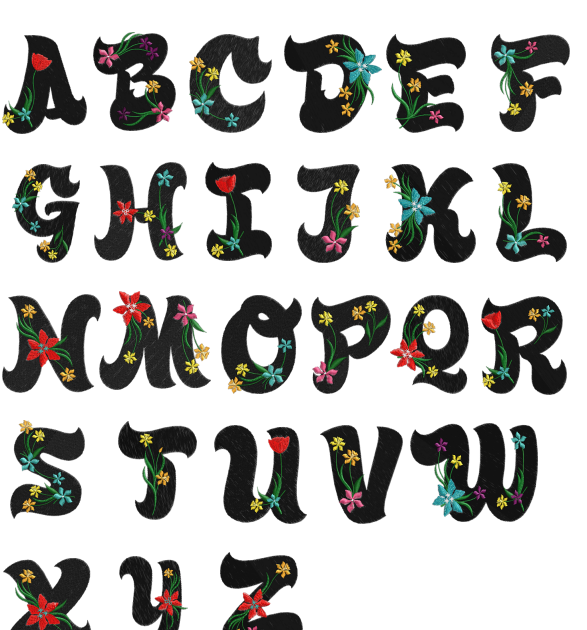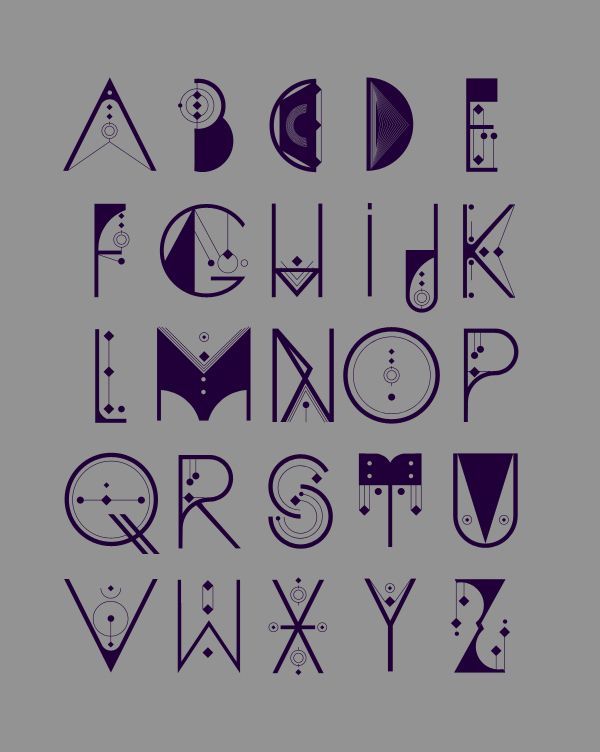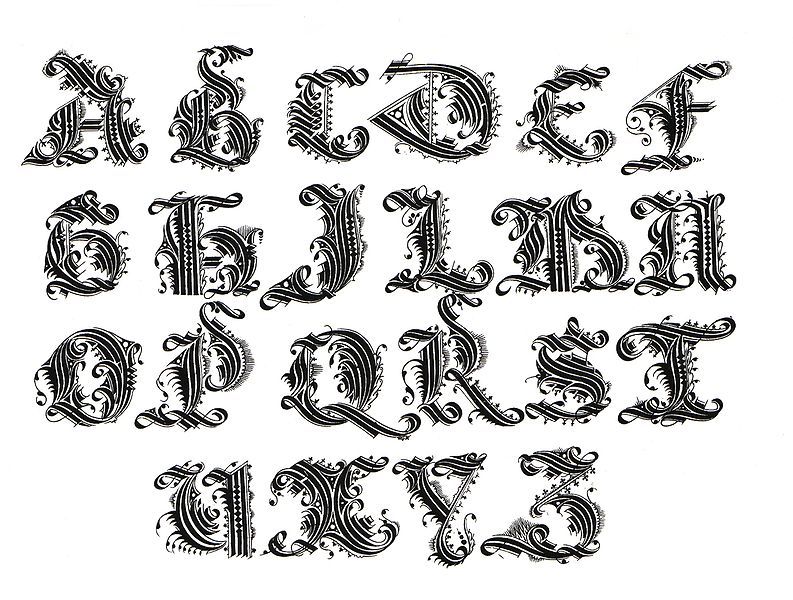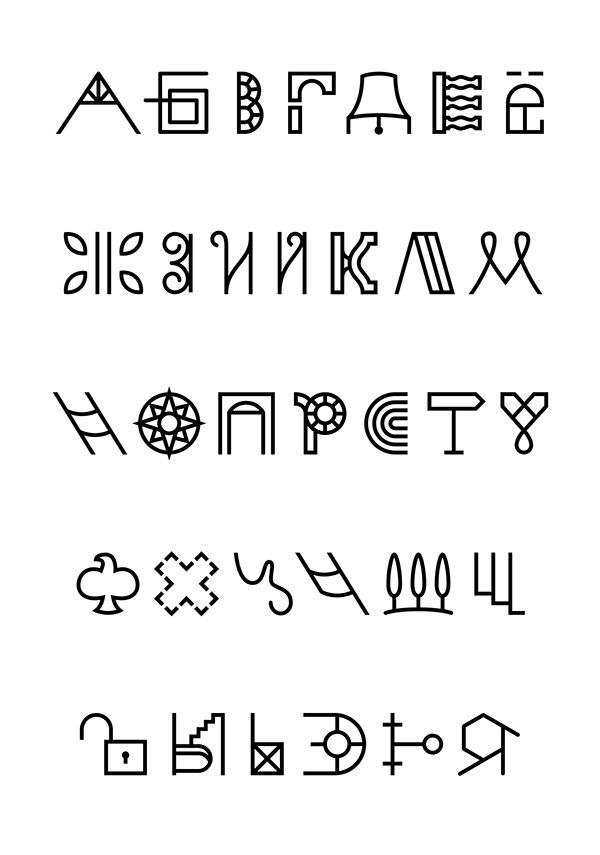
Необычный шрифт букв русского алфавита: шаблоны букв, распечатать и вырезать. Яп
Каллиграфический шрифт картинки — 85 фото
Шрифты для Pilot Parallel Pen
Современная русская каллиграфия
Каллиграфический почерк алфавит для начинающих
Леттеринг буквы русского алфавита
Стили шрифтов для тату
Каллиграфия плакат
Каллиграфия Готика фрактура
Кисть для каллиграфии
Стилизованный шрифт
Каллиграфический шрифт
Каллиграфия кириллица скоропись
Каллиграфические имена на русском
Шрифт каллиграфия кистью кириллица
Леттеринг алфавит английский
Почерк спенсериан
Каллиграфический шрифт Готика
Каллиграфический шрифт цифры
Каллиграфия английский алфавит копперплейт
Каллиграфический шрифт
Современная каллиграфия шрифты
Каллиграфический шрифт
Современная каллиграфия
Каллиграфия копперплейт алфавит
Шрифты леттеринг Готика
Каллиграфический почерк с завитушками
Cursive шрифт
Каллиграфические надписи
Каллиграфия шрифт
Каллиграфия копперплейт алфавит
Каллиграфия брашпеном алфавит
Каллиграфия пером шрифт
Каллиграфия буквы покрас Лампас
Каллиграфический шрифт
Каллиграфия копперплейт алфавит
Шрифт каллиграфия кистью кириллица
Копперплейт шрифт каллиграфия
Леттеринг Готика алфавит
Спенсериан каллиграфия
Каллиграфический шрифт
Фрактура каллиграфия
Каллиграфический почерк алфавит
Каллиграфия в стиле Готика для алфавит
Буквы каллиграфическим почерком русские
Каллиграфический шрифт русский
Каллиграфия русский алфавит прописи
Флориш Готика каллиграфия
Буквы каллиграфическим почерком русские
Шрифты для тату
Красивый шрифт
Каллиграфические буквы английские
Алфавит спенсериан каллиграфия
Каллиграфический почерк английский алфавит
Каллиграфия русского алфавита строчные буквы
Леттеринг на английском Готика
Каллиграфия итальянский курсив прописи
Стиль леттеринг шрифты
Каллиграфия необычные шрифты
Красивая буква а заглавная каллиграфия
Шрифты леттеринг ручкой
Каллиграфия английский алфавит копперплейт
Красивый шрифт на английском
Шрифты для тату
Каллиграфия копперплейт алфавит
Русский алфавит спенсериан каллиграфия
Английские буквы красивым шрифтом
Татарский шрифт
Готический почерк английский
Шрифт копперплейт кириллица каллиграфия
Каллиграфия копперплейт алфавит
Красивый прописной почерк алфавит
Красивые прописные буквы по английскому
Каллиграфия английский алфавит копперплейт
Красивые английские буквы
Шериф красивый на русском
Скоропись каллиграфия алфавит
Каллиграфия английский алфавит копперплейт
Прописи для красивого почерка
Рукописные русские шрифты кистью
Каллиграфические буквы
Шрифт в арабском стиле
Каллиграфичное правописание букв
Spencerian каллиграфия
Каллиграфия Готика фрактура
Каллиграфический шрифт современный
Покрас Лампас каллиграфия алфавит
emailОдна из самых серьезных проблем при создании электронных писем — правильно выбрать шрифт. Вес, высота, ширина, цвет, форма, интервал… Все ли здесь имеет значение? Да, важно все, но самое главное — выбрать читабельный шрифт.
В этой статье мы расскажем, как выбрать лучший профессиональный шрифт для рассылки.
Шрифты HTML-писем: основные правила, которые нужно соблюдать
При выборе оптимального шрифта следует учитывать три базовых правила:
1. Не используйте более двух шрифтов
Если вы используете слишком много шрифтов, ваше письмо будет выглядеть как минимум перенасыщенным, а в худшем — довольно раздражающим. Для одного письма достаточно одного или двух шрифтов. В идеале вообще используется всего один шрифт, но разных размеров: больший — для заголовков, а меньший — для остального контента.
2.
Избегайте применения более двух стилей шрифтаНе смешивайте в письмах обычные, жирные и курсивные стили шрифтов. Если вы используете более двух, рассылка будет выглядеть неаккуратно. Как правило, достаточно одного стиля. Если же вы хотите что-то выделить, можно применить жирный шрифт.
При этом никогда не подчеркивайте текст и не используйте курсив — это противоречит правилам доступности писем.
3. Уделите особое внимание читабельности выбранного шрифта
Основной параметр шрифта вашего контента — читабельность. Это понятие означает возможность отличить одну букву от другой. Естественно, разборчивый текст лучше и быстрее читается, поэтому проверьте, все ли символы четкие, хорошо заметные и различимые.
Какой шрифт самый читаемый? В 2010 году Норберт Шварц и Хюнджин Сонг провели эксперимент по разборчивости шрифта. Результаты были впечатляющими: чтение курсивных и декоративных шрифтов отнимает почти вдвое больше времени, чем стандартных и легко читаемых:
И еще о разборчивости.
.. Существуют два основных типа шрифтов: с засечками и без. Давайте посмотрим, какой из них лучше использовать для email-рассылок.
Какой шрифт выбрать: с засечками или без?
Да, эти типы (гарнитуры) тоже влияют на разборчивость шрифтов электронных писем. В чем заключается разница между ними?
Шрифты Serif (с засечками) можно определить как шрифты с маленькой черточкой в конце каждого символа. Самые популярные шрифты с засечками — Times New Roman и Georgia.
Шрифты Sans Serif (без засечек) — это те, которые не имеют такой декоративной линии в конце символа. Самые популярные веб-безопасные шрифты такого типа — Arial, Trebuchet MS и Helvetica.
В ходе своего исследования я нашла ряд источников, которые утверждают, что шрифты с засечками лучше подходят для рассылок, но я с этим категорически не согласна. Если предположить, что письма просматриваются только в режиме онлайн на десктопных или мобильных экранах, то лучше всего использовать шрифты без засечек — такие символы проще читать с экрана.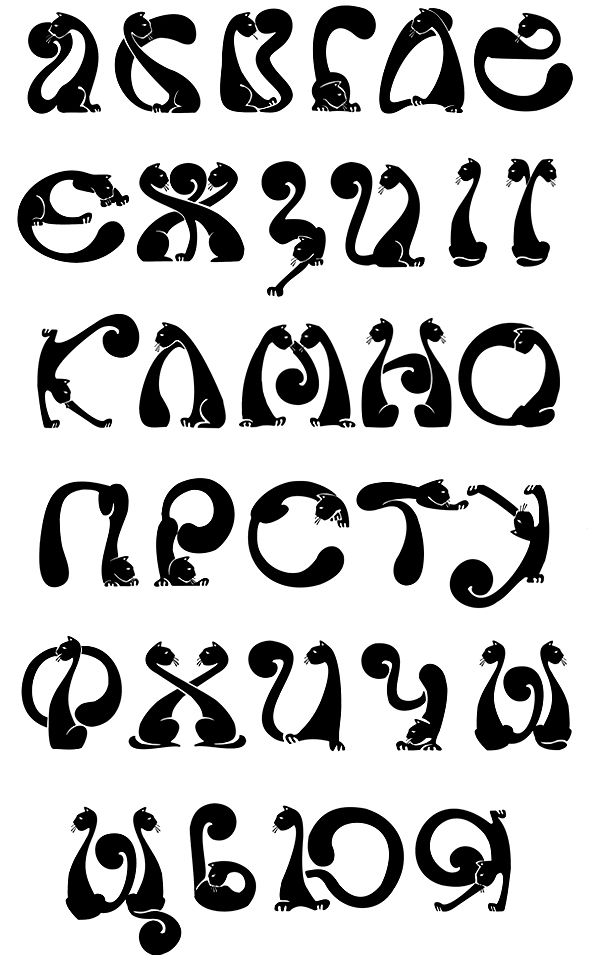
Безопасные шрифты для писем
Вашему вниманию предлагается список из 10 лучших шрифтов, которые можно использовать со 100% гарантией того, что они будут отображаться в электронных ящиках пользователей именно так, как было задумано. Поэтому вы можете спокойно выбрать из этого списка веб-шрифт для своих нужд:
1. Шрифт для писем Arial
Этот шрифт, разработанный еще в 1982 году, входит в пакеты всех версий Microsoft, начиная с Windows 3, и Apple Mac OS X. Отображается всеми почтовыми клиентами. Благодаря терминальным диагональным разрезам выглядит менее механическим по сравнению с другими sans serif.
2. Шрифт для писем Helvetica
Печатный шрифт sans-serif, один из самых применяемых шрифтов, имеет закругленные буквы и широкие прописные буквы. Разработан в 1957 году.
3. Шрифт для писем Times New Roman
Этот безупречный шрифт имеет высокие строчные буквы, слегка уплотненные, короткие нисходящие и восходящие. Создан по заказу газеты «The Times» в 1931 году.
Это один из любимых шрифтов из семейства sans serifs у многих интернет-пользователей и веб-дизайнеров.
4. Шрифт для писем Verdana
Он был разработан для чтения на экранах с низким разрешением. Его главная особенность — высокие и широкие строчные символы.
5. Шрифт для писем Courier / Courier New
Courier был разработан в 1955 году и адаптирован для моноширинного шрифта. Courier New имеет больше точек и запятых, чем оригинальный Courier. Courier является стандартным современным шрифтом, используемым для написания сценариев в киноиндустрии.
6. Шрифт для писем Tahoma
Он похож на Verdana, но имеет более узкие буквы, маленькие кегли и малый интервал между буквами. Используется в качестве экранного шрифта по умолчанию в версиях Windows 95, 2000 и XP.
7. Шрифт для писем Georgia
Он имеет высокие строчные штрихи, которые толще среднестатистических, его цифры органично сочетаются с текстом благодаря одинаковому размеру.
8. Шрифт для писем Palatino
Этот великолепный шрифт был изначально разработан для заголовков, рекламных объявлений и печати. Он шире других шрифтов serif старого стиля и прекрасно подходит для дизайна логотипов.
9. Шрифт для писем Trebuchet MS
Имеет укороченные хвосты для некоторых букв; в полужирном начертании буквы заостренные, а не закругленные, и закругленные точки в прописных и строчных буквах. Появился в 1996 году.
10. Шрифт для писем Geneva
Это обновленная версия Helvetica. Его главное отличие — наличие базового набора лигатур.
Эти шрифты считаются самыми читаемыми современными шрифтами и одними из лучших современных шрифтов для использования в email-дизайне.
Кастомные шрифты
Бывает так, что вы хотите — или должны — использовать в письме собственный уникальный шрифт. Например, для соблюдения стиля бренда. Или если нужно создать праздничное письмо для соответствующего случая.
Напоминаем, что вы можете загружать кастомные шрифты в свой аккаунт Stripo и использовать их в рассылках.
Используйте кастомные шрифты в рассылках — соблюдайте стиль бренда
Присоединяйтесь к Stripo
Но при этом мы настоятельно рекомендуем предварительно тестировать их отображение в различных комбинациях почтовиков, девайсов и ОС. Это можно сделать при помощи нашего встроенного инструмента тестирования.
Важно отметить:
Если почтовый клиент не поддерживает какой-либо шрифт, то последний не будет отображаться неправильно — он просто будет заменен дефолтным шрифтом.
Вот список дефолтных шрифтов для самых популярных почтовиков:
-
iCloud Mail использует Helvetica в качестве дефолтного;
-
Gmail применяет Arial;
-
Microsoft Outlook самых доисторических версий часто использует Calibri;
Размер шрифта
Не существует такого понятия, как лучший размер шрифта. Дело в том, что разные шрифты часто имеют разную высоту символов.
В результате один и тот же размер, к примеру 16 пикселей, выглядит очень неодинаково в зависимости от выбранного семейства шрифтов.
Я создала в редакторе Stripo специальный шаблон, который позволяет сравнить разные шрифты одних и тех же размеров. Вот результаты:
Выберите любой из них на ваш вкус и используете во всех электронных email-кампаниях, чтобы ваши письма всегда были разборчивыми и соответствовали стилю бренда.
Мы советуем сразу выбирать шрифты и их размеры, как только вы начинаете работу с новым шаблоном — настройки будут применены сразу ко всему письму. Это существенно сэкономит время, так как вы избавитесь от необходимости настраивать шрифт для каждой части письма.
Знаете ли вы, что в Stripo можно устанавливать разные размеры шрифтов для мобильных и десктопных устройств? Например, вы используете 14 пикселей для десктопной версии и 16 пикселей, если письмо открывается на смартфоне.
Настройка размера шрифта для десктопных устройств
-
войдите во вкладку «Оформление»;
-
перейдите в раздел «Общие настройки»;
-
выберите нужный шрифт в выпадающем меню.
Кастомные шрифты, которые вы ранее добавили в свой профиль Stripo, тоже отобразятся в этом списке; -
установите межстрочный интервал;
Попробовать Stripo
Настройка размера шрифта для мобильных
-
зайдите во вкладку «Оформление»;
-
перейдите в раздел «Адаптивность»;
-
установите размеры шрифта для хедеров и футеров, областей контента, пунктов меню и кнопок.
Поработайте над отображением ваших писем на мобильных, и они будут легко читаемыми на любом устройстве
Присоединиться к Stripo
Межстрочный интервал
Межстрочный интервал — это расстояние между строками по вертикали. Он измеряется в процентах от размера шрифта.
Вы можете установить желаемый интервал для своих писем в тех же вкладках и разделах, в которых только что настроили размер шрифта.
Некоторые источники утверждают, что лучший межстрочный интервал — 150%.
Но если учесть рекомендации по доступности писем, то оптимальный интервал варьируется от 150% до 200%.
(текст письма с одиночным интервалом)
(текст письма с интервалом 1,6)
Ссылки
Не стоит использовать другой шрифт, чтобы привлечь внимание читателей к ссылкам. И ни в коем случае не добавляйте ссылки без анкорного текста. Текст анкора должен пояснять, куда ведет данная ссылка, и быть органичной частью текста. Избегайте слов «здесь» или «ссылка» в качестве анкорного текста. Они слишком короткие и слишком общие, чтобы быть интересными.
Одно из лучших решений — сделать ссылки того же цвета, что и логотип. Это выглядит великолепно, вот посмотрите:
(Источник: письмо от Epilepsy Foundation)
Можно также подчеркнуть ссылки, если вы посчитаете это нужным или если такие ссылки соответствуют дизайну вашего письма.
Хотя из соображений доступности писем мы очень не советуем подчеркивать ссылки — это дезориентирует людей с дислексией.
Кнопки
Кнопки — это те же ссылки, но в более интерактивной для пользователей форме. Лучше использовать в письмах и ссылки, и кнопки. Если вы добавляете ссылку, которая приведет читателей к статье в блоге, вы можете сделать ее текстовой. Но если ссылка нужна, чтобы попробовать ваш продукт, то лучше использовать кнопки.
Что касается цвета кнопок, каких-то определенных правил здесь нет. Мы советуем положиться на цветовую психологию и постараться не разрушить концепцию дизайна слишком «кричащей» цветопередачей.
То же относится и к шрифтам для кнопок: четких правил не существует. Просто убедитесь, что тексты кнопок достаточно разборчивы.
Убедитесь, что цвет текста гармонирует с цветом кнопки и что он достаточно заметный и читаемый. Также проверьте, правильно ли расположен текст на кнопке — он не должен выползать за ее края.
Вот тот случай, когда кнопка смотрится отлично:
(Источник: email-шаблон Stripo)
Важно отметить:
При помощи Stripo в кнопки можно даже добавлять пробелы, чтобы между текстом и границами кнопки оставалось свободное пространство.
Это делает их более читабельными.
Как это сделать? Поработайте над параметрами внутренних отступов во вкладке «Кнопка».
Вы также можете отдельно настроить размер шрифта кнопок для мобильной версии.
Для этого вам нужно:
-
зайти во вкладку «Оформление»;
-
перейти в раздел «Адаптивность»;
-
установить размер текста кнопки, чтобы сделать его разборчивым на мобильных экранах. Оптимальный размер — 16px или крупнее;
-
включить «Кнопки на всю ширину», чтобы сделать кнопки шире на смартфонах. У полноразмерных кнопок больше шансов быть замеченными.
Делайте кнопки CTA заметными и интерактивными на любом устройстве
Присоединиться к Stripo
Текст поверх баннера
Это возможность использовать необычные и декоративные шрифты, которые вы не можете использовать как основной шрифт для текста.
А поскольку текст поверх баннера является частью изображения, то он не утратит своей декоративности ни в одном почтовом клиенте. То есть здесь можно делать что угодно.
Обратите внимание, что при этом лучше выбирать разборчивый шрифт и не писать слишком много текста на баннере. Будьте лаконичны.
Впрочем, выбор зависит прежде всего от ваших идей и от стиля дизайна.
Использование декоративных шрифтов для баннера в Stripo
Присоединиться к Stripo
Цвет шрифта
Здесь достаточно соблюдать всего два правила:
1. Придерживайтесь минимального количества цветов
Используйте только те цвета, которые присутствуют в цветовой схеме вашего бренда. Хотите использовать более трех цветов? Забудьте и думать об этой идее — она сделает текст нечитаемым.
Если вы хотите выделить какое-то предложение или фразу, просто используйте жирный шрифт: выделять другим цветом — так себе решение.
Пример удачного сочетания цветов в письме.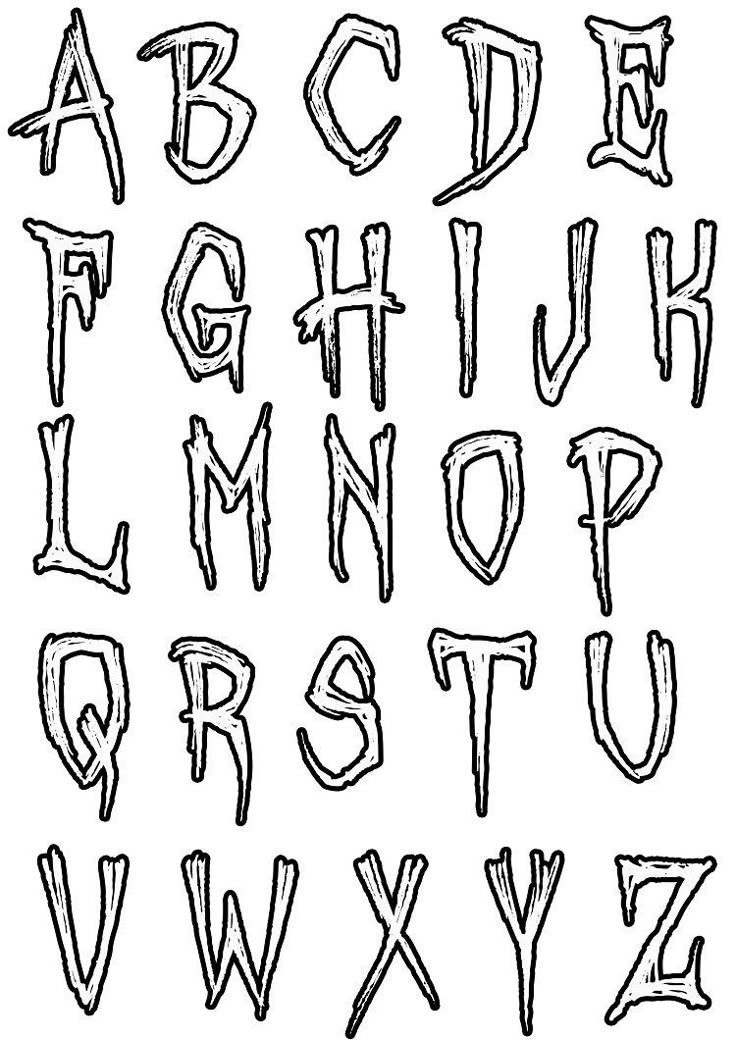
(Источник: письмо от Victoria’s Secret)
2. Используйте контрастные цвета
Если вы собираетесь использовать яркие цвета, как делают многие в праздничных рассылках — обязательно выбирайте контрастные. Не помещайте красный текст поверх зеленых кнопок, не используйте белый на сером. Это может показаться красивым для людей с хорошим зрением, но дальтоники могут вообще не разобрать текст.
Обычно дизайнеры используют для контента черный или темно-серый цвета, потому что их удобнее читать. Единственное исключение — если у вас черный фон. В этом случае используйте белый шрифт. Не используйте светло-серый, потому что его трудно читать.
HTML-теги для форматирования текста
Те email-маркетологи, которые предпочитают конструкторы шаблонов, могут форматировать текст прямо в этом инструменте.
Тем, кто любит кодировать письма с нуля, могут понадобиться следующие теги.
<strong> text here </strong> or <b> text here </b>
<ul>
<li> point 1 </li>
<li> point 2 </li>
<li> point 3 </li>
</ul>
<i> text here </i> or <em> text here <em>
<small> text here </small>
<mark> text here </mark>
<p> text here </p>Написание текста справа налево
Более 550 миллионов человек говорят на языках, в которых используется написание справа налево.
Скрипт RTL (Right to Left) — это нечто больше, чем просто обратный порядок слов.
Например, здесь не нужно оборачивать числа, иностранные слова и т.д. Все знаки препинания, которые вы обычно ставите в конце строки, фактически начинают ее. Мы не будем вдаваться в подробности: вы можете ознакомиться со всеми рекомендациями по режиму RTL в нашем блоге, статья «Как с помощью Stripo писать текст письма справа налево».
В ней мы также рассказываем, как активировать опцию RTL в Stripo, чтобы вы могли использовать в рассылках RTL-скрипты без навыков программирования.
Создавайте письма в формате RTL максимально быстро
Присоединиться к Stripo
Требования к доступности
Если вкратце, то мы должны учитывать эти рекомендации по ряду причин:
-
чтобы люди с цветовой слепотой могли читать наши рассылки;
-
чтобы люди с нарушениями зрения могли слушать письма при помощи программ чтения экрана;
-
чтобы пользователи, которые очень заняты и проверяют почту во время вождения или приготовления еды, могли попросить Siri «прочитать» входящие сообщения и таким образом прослушать наши письма;
-
чтобы позволить читать наши рассылки дислексикам — многие люди, страдающие дислексией, не знают об этом, но чтение неадаптированных текстов для них совершенно невыносимо.
Итак, вот основные рекомендации по созданию доступных текстов писем:
-
Учитывайте цветовые контрасты.
-
Выравнивайте тексты по левому краю, чтобы облегчить восприятие текста дислексиками — избегайте выравнивания по центру.
-
Всегда добавляйте знаки препинания в конце каждого пункта маркированного списка. Да, это может противоречить правилам грамматики, но таким образом мы сделаем письма более разборчивыми — и по крайней мере одного человека счастливее.
-
Придерживайтесь размера шрифта 14 пикселей или больше.
-
Не подчеркивайте тексты.
-
Избегайте курсива. Если вам нужно выделить какую-либо часть текста, используйте только жирный шрифт!
-
Не используйте сплошной капс!
Подробности о том, как создать доступное письмо, вы узнаете в нашем блоге в специальной статье о доступности.
Какой шрифт лучше использовать для рассылок?
Не существует такого понятия, как лучший шрифт для Gmail, Outlook или любого другого почтового клиента. На самом деле все зависит от языка, на котором мы говорим. То есть можно сказать, что в разных странах предпочтения варьируются по причине языковых особенностей.
По результатам многочисленных экспериментов, проведенных маркетинговой командой eSputnik, лучшие шрифты для писем в русскоязычных странах — Arial и Tahoma. Arial — идеальный выбор для тех, кто проводит email-кампании на русском языке. Tahoma отлично смотрится как в массивных, богатых контентом письмах, так и в коротких сообщениях.
Helvetica — самый популярный шрифт в англоязычных странах. На втором месте Arial.
Чтобы выбрать наиболее разборчивый шрифт с учетом особенностей вашего алфавита, можно протестировать все веб-безопасные шрифты, как это сделали мы. Вы можете попросить друзей и коллег помочь вам с тестированием.
Я сделала в редакторе Stripo шаблон с одинаковым текстом и размером (18px), но разными шрифтами.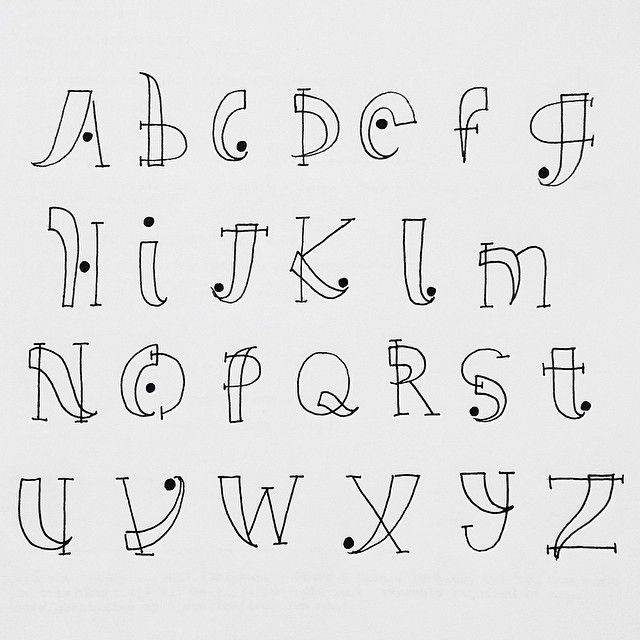
И вот результаты — просто сравните шрифты и выберите тот, который максимально соответствует вашим потребностям:
В завершение
Учитывая все вышеизложенное, мы можем сказать вот что: не существует профессиональных шрифтов, которые были бы читабельными и привлекательными на всех типах устройств. Всегда приходится выбирать:
-
Georgia и Times New Roman слишком узкие; -
Courier New широкий… может быть, даже слишком широкий для электронного письма;
-
Arial легче, чем Helvetica;
-
Verdana и Tahoma невозможно различить.
И еще раз. Помимо правильного выбора шрифта, ни в коем случае нельзя забывать о вышеизложенных требованиях доступности.
Stripo предлагает множество веб-безопасных и декоративных шрифтов. Вы также можете загрузить собственные
Начать работу
Turnitin, Плагиат и распознавание кириллицы Е для E
При просмотре литературы на Turnitin.
com всплыл интересный юникодный кусочек. В одной статье Туритнина обсуждаются попытки обхода Тертинина и их контрмеры. Знатоков Юникода не удивит, что латиницу Е (т.е. нашу Е) нужно заменить на кириллицу Е или греческую Е. Технический термин для этого визуальный спуфинг
Теоретически, инструктор увидит «the» как «the», но на самом деле будет достаточно отличаться, чтобы НЕ быть помеченным. Очевидно, Turnitin увидел это и предлагает свою контрмеру.
Один из приемов заключается в замене общего символа, такого как «е», в тексте их статьи символом иностранного языка, который выглядит как «е», но на самом деле отличается от него (например, кириллица «е»). Этот метод не работает, потому что наши алгоритмы заменяют такие символы соответствующими стандартными английскими символами. Специальный символ по-прежнему будет отображаться в отчете об оригинальности; однако слово, в котором оно находится, будет сопоставлено со словами, содержащими все символы, похожие на этот символ.Это позволяет нам показывать вам совпадения со словами как со специальным символом, так и со стандартным символом.
Проверка за пределами Turnitin
Я рад, что Turnitin справляется с этой задачей, но есть несколько приемов для инструкторов, которые не пользуются этой службой, чтобы распознавать кириллические/греческие буквы, маскирующиеся под английский алфавит. А именно:
- Используйте проверку орфографии, чтобы найти ошибки в словах, которые выглядели правильно написанными.
- Переключиться на декоративный шрифт, НЕ содержащий греческих и кириллических букв.
Один из способов — использовать или включить функцию визуальной проверки орфографии в Word 9.0022 и другие инструменты. Это тот, который ставит красные волнистые линии под орфографической ошибкой. Например, на изображении ниже показаны три варианта слова «Елизавета» с буквами «Е» на латинице, кириллице и греческом языке. Они выглядят одинаково, но только один из них не подчеркнут красной волнистой линией — это тот, что с английской буквой E.
Другие скрывают греческие и кириллические буквы E и, таким образом, вызывают уведомления от проверки орфографии Microsoft Word.
Еще одна хитрость заключается в том, чтобы переключиться на необычный шрифт . Обычные шрифты, такие как Times New Roman, Arial и Verdana, содержат греческие и кириллические символы, но во многих декоративных шрифтах они отсутствуют. В некоторых случаях греческая/кириллица E, видимая в одном шрифте, будет преобразована в рамку/вопросительный знак или другой странный символ, указывающий, что система не обрабатывает символ как английскую букву.
Однако в некоторых случаях неанглийская буква E может отображаться аналогичным шрифтом, содержащим этот символ. Вот что происходит в этом примере Comic-Sans. Однако, если вы внимательно посмотрите, вы увидите, что только центральная заглавная буква Е закруглена, как и другие буквы. Неанглийские буквы E в двух других написаны прямо вверх и вниз, потому что они написаны другим шрифтом.
Есть и другие подобные тесты, которые вы можете выполнить, но в результате большинство технологий на самом деле не настроены для интеграции кириллического/греческого текста с английским текстом, и для сообразительного инструктора, ищущего спуфинг, это хорошая вещь.
Рослиндейл Кириллица | Искусство коммуникации
Экспонат
Йована Йоцич переносит остроконечный контраст латинского шрифта De Vinne в кириллицу для DJR.
Ответы Йованы Йоцич.
Предыстория: Roslindale — это универсальный текстовый и акцидентный шрифт с засечками, который начинался как новая интерпретация De Vinne, причудливого викторианского шрифта, первоначально опубликованного в 1890 от Central Type Foundry. Его уникальное отношение исходит из реверберации острых заостренных засечек на фоне выпуклых круглых форм. Оказывается, этот контраст шипов и пятен естественно подходит для кириллицы, которая имеет больше возможностей для этих специфических функций по сравнению с латиницей.
В моей интерпретации латинского дизайна типографа Дэвида Джонатана Росса для кириллицы я не упустил возможности усилить это сопоставление.
Дизайнерское мышление: Roslindale с 2017 года превратился в обширное семейство шрифтов для использования в редакциях и брендинге. Как пользователь кириллицы, я был рад поднять его универсальность на новый уровень, расширив его языковую поддержку. Росс и я согласились, что лучшим решением будет баланс между потребностями шрифта и уникальными требованиями кириллицы, и я стремился найти этот баланс.
Задачи: Оставаться верным уже установленному визуальному стилю, адаптируя его к новой системе письма. Это неизменно самый сложный аспект любого языкового выражения. Строение кириллических букв и их общее ощущение при наборе в текст довольно сильно отличается от латиницы. Чтобы соединить их как можно естественнее, я почувствовал необходимость расширить свой словарный запас форм и ввести некоторые новые формы, которых нет в латыни.
Любимые детали: Одной из самых захватывающих частей проекта был курсив. Курсивное построение позволило мне играть и придумывать детали, которые также повлияли на многие решения, принятые в романе. Стилистические альтернативы позволяют пользователю легко использовать латинские формы в курсивных шрифтах и наоборот, предлагая необычные возможности для стилистических вариаций.
Временные ограничения: На протяжении всего процесса проектирования мы с Россом регулярно встречались, просматривали корректуру и обсуждали наилучший способ сбалансировать потребности шрифта и потребности сценария. Поскольку это не было заказано конкретным клиентом, у нас был гибкий срок, который позволил нам изучить различные возможности дизайна, не беспокоясь о временных ограничениях.
Конкретные требования к проекту: Нанесение кириллицы для одного стиля достаточно сложно, но Roslindale Cyrillic доступна в серии компактных гирь для дисплеев — от сверхлегких до ультра — а также в более ограниченном наборе более прочных палубных и рулежных гирь.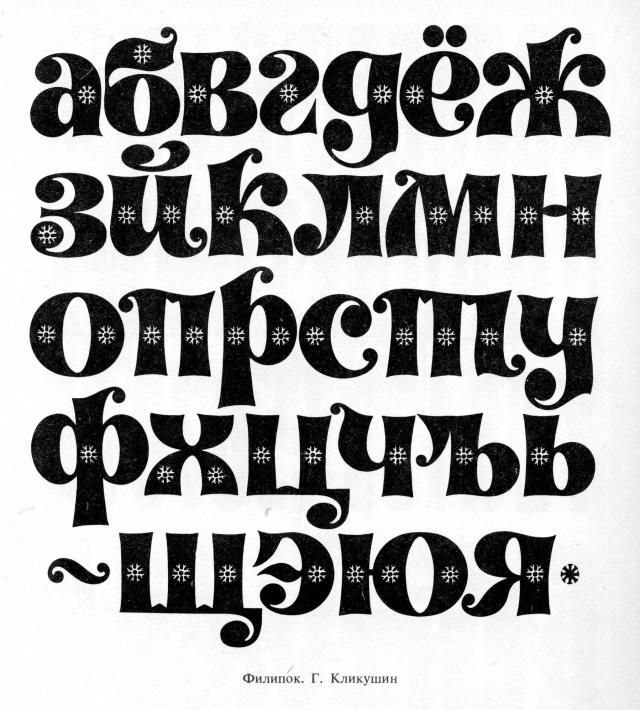